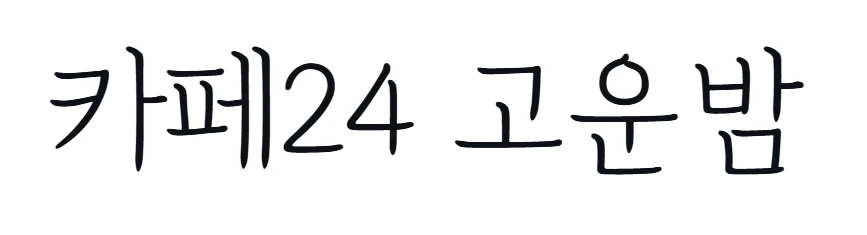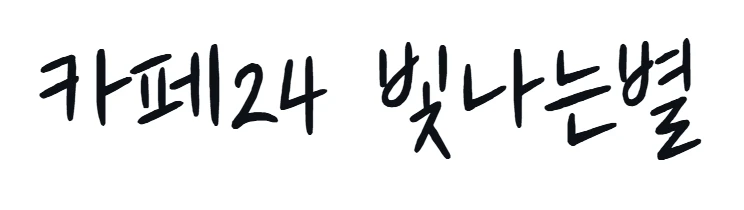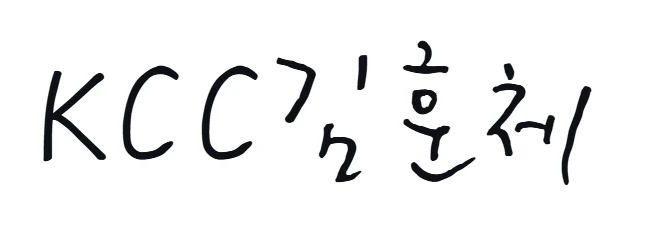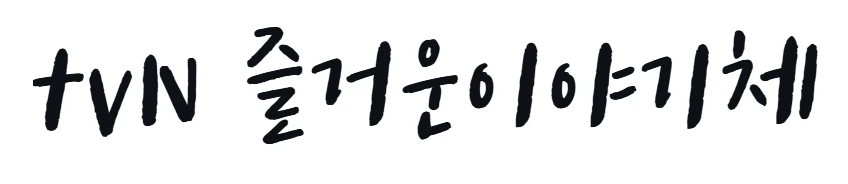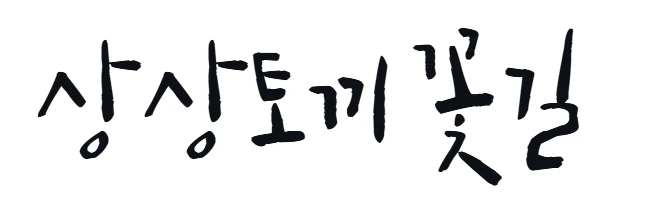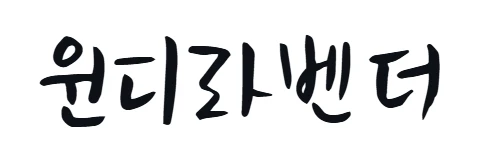
아름다운 손글씨 폰트로 디자인의 품격을 높이고 싶지만 저작권 걱정 때문에 망설이셨죠?
이 글에서 상업적 이용이 가능한 무료 한글 필기체 폰트들을 소개해 드릴게요!
감성 가득! 추천 한글 필기체 폰트 📝
제가 직접 사용해보고 만족했던, 그리고 많은 분들이 사랑하는 감성적인 한글 필기체 폰트들을 소개해 드릴게요. 각각의 폰트마다 개성이 뚜렷해서 다양한 분위기를 연출하는 데 정말 좋더라고요. 이 폰트들은 모두 상업적 이용이 가능해서 개인 프로젝트는 물론, 회사 업무나 클라이언트 작업에도 부담 없이 사용할 수 있답니다. 👍
인기 무료 필기체 폰트 상세 분석 📊
자, 그럼 이제 제가 추천하는 필기체 폰트들을 하나씩 자세히 살펴볼까요? 각 폰트의 특징과 저작권 요약 내용을 표로 정리해 보았으니, 필요에 따라 확인해 보세요!
| 카페24 고운밤, 빛나는 별 | 감성적인 필기체로 디자인에 따뜻하고 부드러운 느낌을 더해줍니다. | 개인 및 기업 사용자 모두 무료 사용 가능, 수정 및 재배포 자유. 단, 폰트 자체 유료 판매 금지. |
| 미생체 (김태호PD 글씨체) | 김태호 PD의 손글씨를 본떠 만든 폰트로, 친근하고 개성 있는 느낌을 줍니다. | 저작권으로부터 완전히 자유로움. 단, 유료 양도 및 판매 금지. |
| 윈디라벤더체 | 부드럽고 자연스러운 필기감으로, 서정적이고 아련한 분위기를 연출합니다. | 개인 및 상업적 이용 모두 무료, 자유로운 배포 가능. 폰트 유료 판매 및 문자 추출 금지. |
| KCC김훈체 | 힘 있고 붓글씨 느낌이 나는 폰트로, 제목이나 강조 문구에 사용하기 좋습니다. | 출처(저작가)만 밝히면 상업/비영리 목적 이용 및 저작물 변경 가능. |
| 상상토끼 꽃길 | 캘리그래퍼 상상토끼 용이 작가의 붓글씨 기반 폰트로, 감성적이고 따뜻한 느낌이 특징입니다. | 개인/기업 상업적 이용 자유. 재배포 가능, 유료 재판매 및 폰트 파일 수정 불가. |
| tvN 즐거운이야기체 | tvN의 고유 글씨체로, 깔끔하면서도 정감 있는 느낌을 줍니다. | 개인 및 기업 모두 무료 사용. 재배포 시 출처 표기 필수. 폰트 임의 수정, 변경, 판매 금지. |
| 더페이스샵 잉크립퀴드체 | 손글씨 느낌이 강한 폰트로, 자연스럽고 독특한 감성을 표현하기 좋습니다. | 개인/상업적 용도 모두 이용 가능. 변형 금지 규정 준수 시 재배포 및 활용 가능. |
폰트 활용 팁: 나만의 디자인 만들기 🎨
무료 폰트를 활용하면 정말 다양한 디자인을 시도해 볼 수 있어요. 제가 몇 가지 팁을 드리자면:
- 제목 폰트: KCC김훈체나 tvN 즐거운이야기체처럼 가독성이 좋고 개성 있는 폰트를 사용해 보세요. 시선을 확 사로잡을 수 있답니다.
- 본문 폰트: 고운밤, 빛나는 별이나 미생체처럼 부드럽고 편안한 폰트를 사용하면 독자들이 내용을 읽는 데 피로감을 덜 느낄 거예요.
- 감성 디자인: 상상토끼 꽃길이나 윈디라벤더체는 엽서, 초대장, 감성적인 카드뉴스 등에 활용하면 그 매력이 배가 된답니다.
- 강조 문구: 문장 내에서 특정 단어나 구절을 강조하고 싶을 때, 다른 필기체 폰트를 섞어 사용하면 시각적인 재미를 줄 수 있어요.
저도 개인적으로는 여러 폰트를 조합해서 저만의 개성을 표현하는 걸 좋아하는데, 이 폰트들 덕분에 작업이 훨씬 즐거워졌어요! 여러분도 이 폰트들을 활용해서 나만의 스타일을 찾아보시는 건 어떨까요? 😊